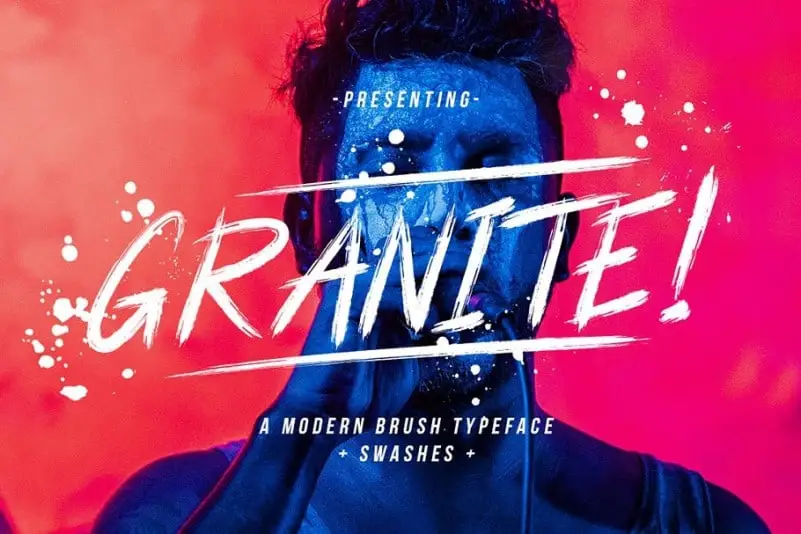
Granite Brush Font – Download Grátis
A Granite Brush Font é uma fonte script criada por Hamilton, caracterizada por seu estilo elegante e sofisticado. Ela segue uma abordagem contemporânea na design, trazendo um toque natural comum e menos rigor no fundo de linha. Esta font foi feita à mão e possui um acabamento autêntico que transmite um look inspirado em moda street e muito parecido com o uso do estilo do esporte extremo. Perfetamente compatível para logos, cabeçalhos, títulos, impressões, roupas e outros possibilidades criativas, Granite Brush é a font perfeita que reúne elegância e simplicidade. Uma opção ideal para designers em busca de uma fonte script com um toque vibrante e natural. A Granite Font é uma escolha ótima para quem deseja dar um toque único e moderno às suas criações visuais.